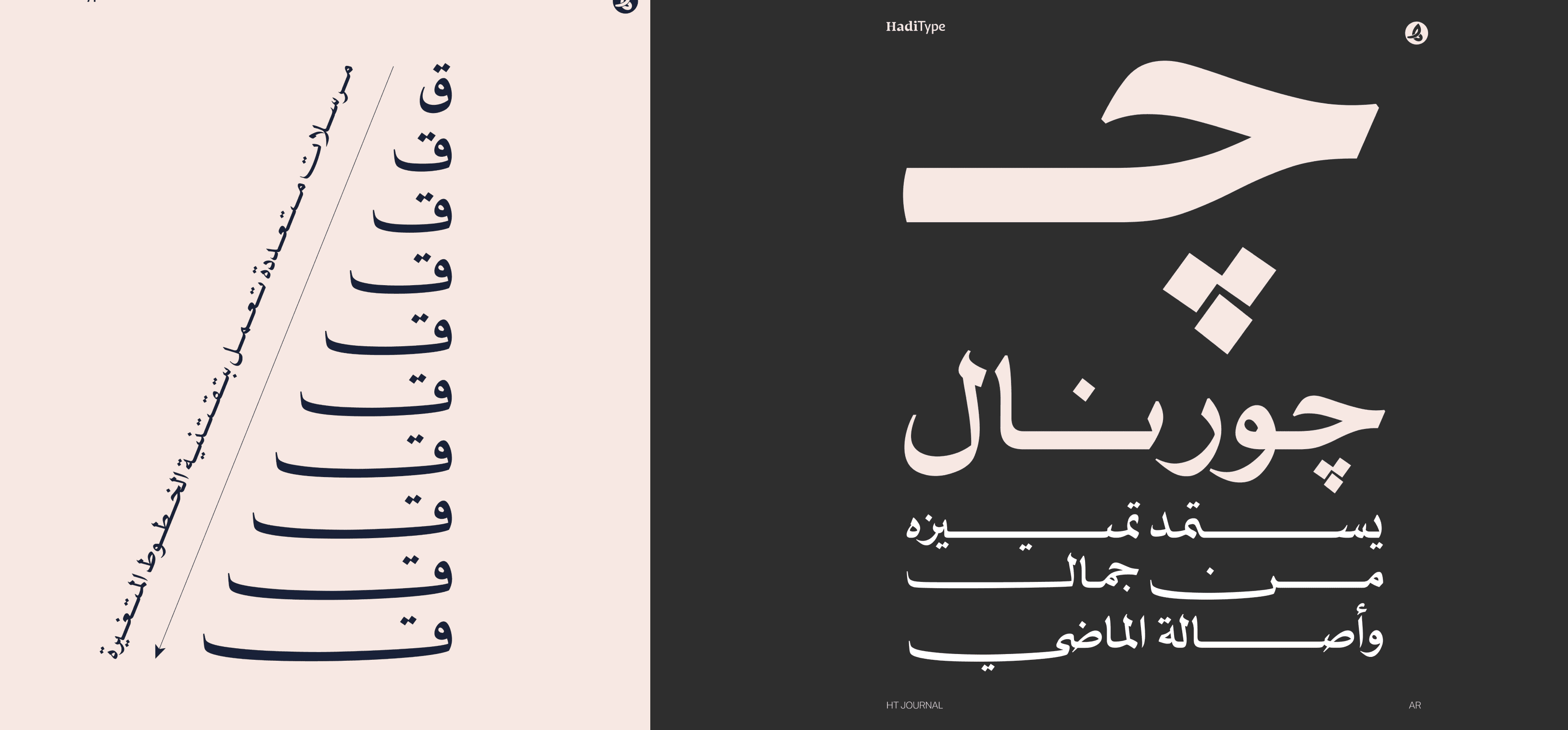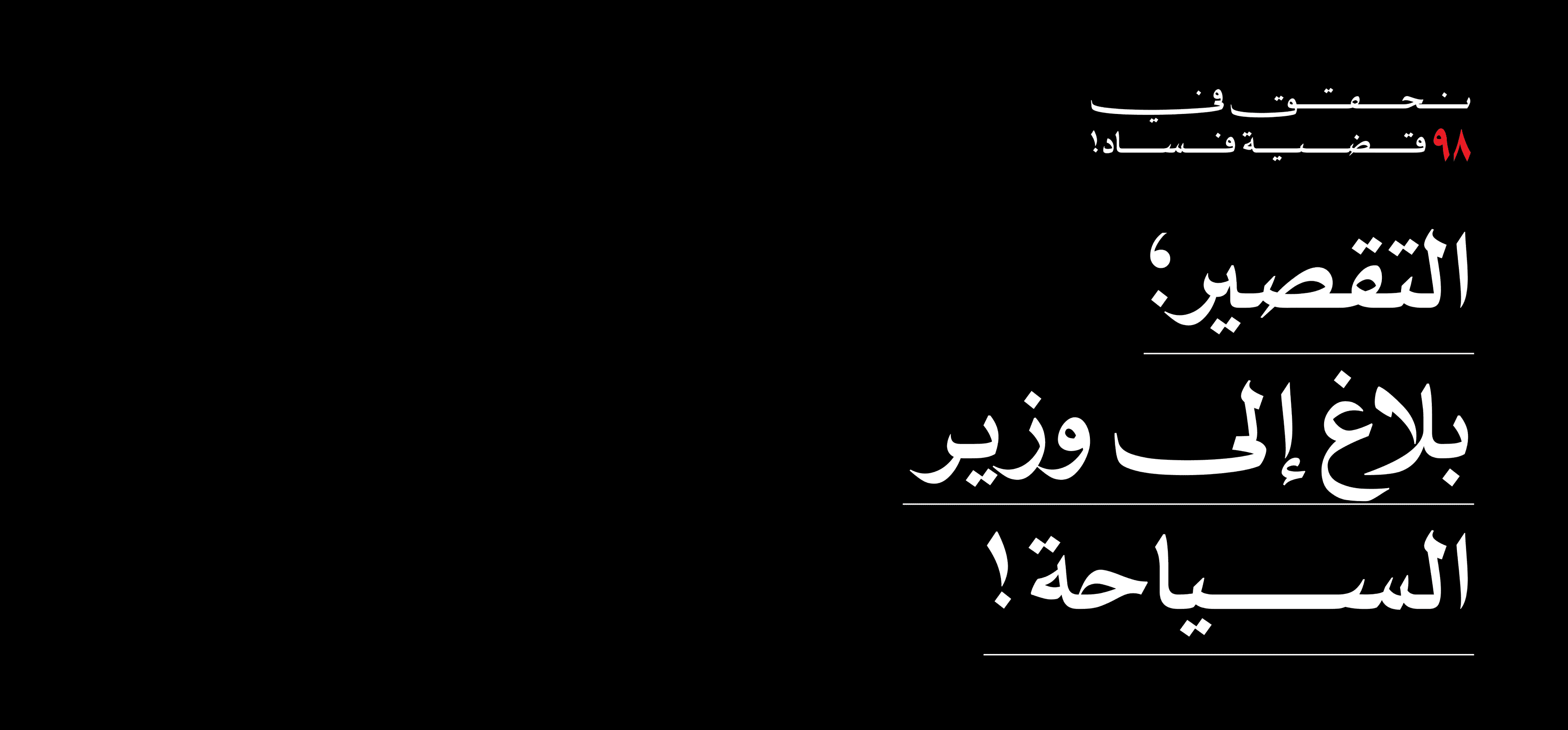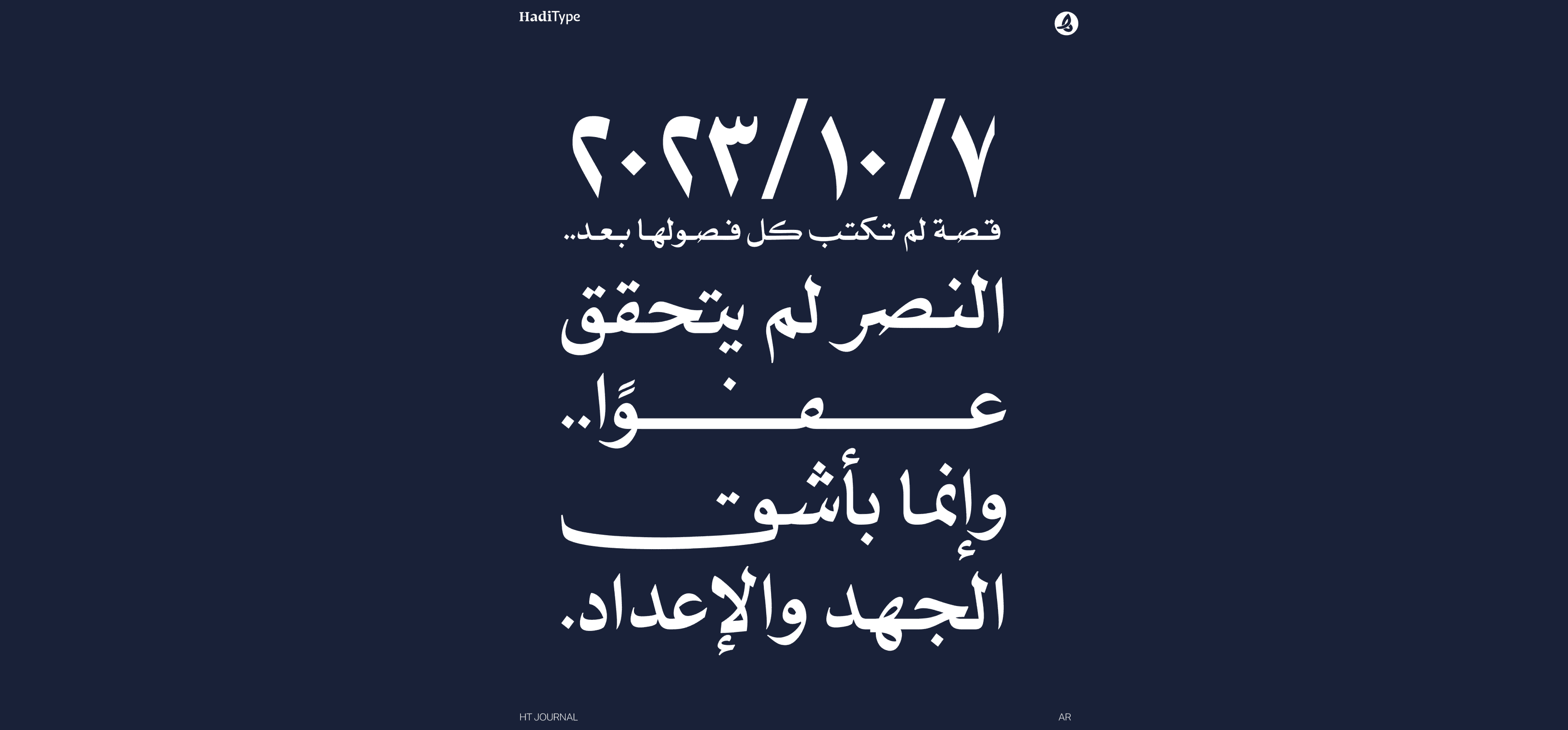
خط HT جورنال – HT Journal Font
خط عربي مستوحى من عناوين الصحف المصرية المميزة بين الستينيات والثمانينيات، يعكس روح الصحافة الكلاسيكية بأسلوب عصري.
يأتي بوزن واحد فقط، لكنه يستخدم تقنية الخطوط المتغيرة (Variable Font) ليمنح تنوعًا بصريًا فريدًا بين الحروف وانتقالاتها.
مثالي لعناوين التحرير، التصميمات الطباعية، والمشاريع التي تبحث عن طابع صحفي تراثي بلمسة تقنية حديثة.